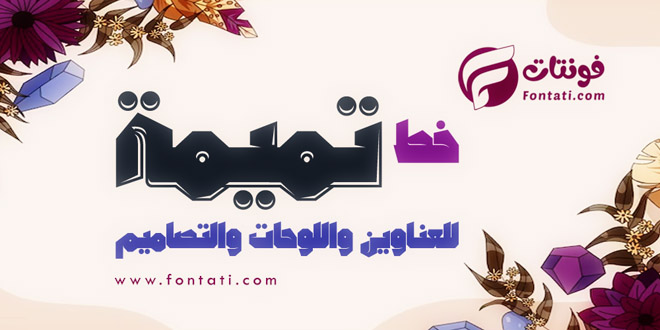
خط تميمة وزنين (سميك وَ بارز) للعناوين واللوحات والتصاميم .. خط تميمة (Tamema) هو خط عربي إبداعي بارز وسميك، صُمم خصيصاً للعناوين القوية واللوحات الفنية والتصاميم الحديثة، ومن مميزات خط تميمة: يأتي بهيكل سميك وواضح، يتوفر بنمطين أساسيين هما الأسود (Black) والمجسم أو البارز (Embossed)، يدعم التصاميم المطبوعة والرقمية وصفحات الويب، يناسب إعلانات الطرق والشعارات وعناوين الكتب.